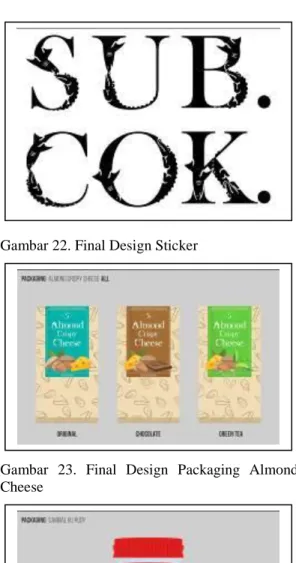
PERANCANGAN TYPEFACE
BERTEMAKAN SIMBOL IKAN SURA DAN BUAYA KOTA SURABAYA
Abstrak
Surabaya merupakan kota yang memiliki latar belakang budaya dan seni yang sangat kental. Kesenian khas kota Surabaya seperti Ludruk, Gending Jula-Juli Suroboyo, Tari Remo, Kentrung, Okol, Seni Ujung, Besutan, Upacara Loro Pangkon, Tari Lenggang Suroboyo dan Tari Hadrah Jidor semakin berkembang menjadikan kesenian tradisional dan modern saling melengkapi membentuk keragaman kesenian kota Surabaya. Di zaman modern ini kesenian visual di kota Surabaya seperti halnya seni tipografi semakin berkembang pesat. Tipografi merupakan mengalami perkembangan secara variatif . Tidak hanya pembuat tipografi vernacular yang bentuk tipografi tersebut bukanlah jenis tipografi yang dihasilkan melalui proses komputerisasi atau berasal dari jenis huruf (typeface) yang sudah ada melainkan bentuk tipografi yang dihasilkan oleh masyarakat sekitar dengan cara manual, tipografi yang melalui proses komputerisasi atau typeface mulai banyak di ciptakan oleh masyarakat kota Surabaya. Namun dari sekian banyak pembuat tipografi vernacular atau typeface di Surabaya masih jarang yang mengangkat tema Surabaya sebagai gagasannya. Perancangan typeface dengan menggunakan simbol ikan sura dan buaya kota Surabaya sebagai gagasannya ini bertujuan untuk Memperkenalkan kota Surabaya kepada masyarakat lokal maupun internasional melalui tipografi dan untuk memperkaya bentuk typeface di Indonesia.
Kata Kunci : Typeface, Tipografi, Simbol Kota Surabaya Abstract
Surabaya is a city that has an authentic cultural background. The cultural product from Surabaya such as Ludruk, Gending Jula-Juli Suroboyo, Tari Remo, Kentrung, Okol, Seni Ujung, Besutan, Upacara Loro Pangkon, Tari Lenggang Suroboyo and Tari Hadrah Jidor have developed. Traditional and modern art are forming together into the diversity of art in Surabaya. Moreover, visual art in Surabaya such as typography has rapidly developed nowadays. Typography is a part of visual communication design. Currently, the form of typography is developing in a variation. People start to create both of vernacular typography which is a manual typography and typeface which is a typography that is made by computerization. However, there is only few of the typography creator use the theme of Surabaya as their ideas. Furthermore, typeface that uses the theme of Surabaya aims to introduce Surabaya into both local and international society. In addition, this typeface could enrich the variety of typography in Indonesia.
Keyword: Typeface, Typography, Symbol of Surabaya
PENDAHULUAN
Di Kota Surabaya, dikenal sebagai kota yang memiliki latar belakang budaya dan seni yang sangat kental, kesenian tradisional dan modern saling melengkapi membentuk keragaman kesenian Kota Surabaya. Ludruk menjadi maskot budaya khas Kota Surabaya, terutama tari Ngeremonya. Ludruk sudah ada sejak zaman Jepang sekitar tahun 1942. Dan menjadi sangat popular di Kota Surabaya sejak zaman revolusi. Kesenian khas Kota Surabaya yang lainnya seperti Gending Jula-Juli Suroboyo, Tari Remo, Kentrung, Okol, Seni Ujung, Besutan, Upacara Loro Pangkon, Tari Lenggang Suroboyo dan Tari Hadrah Jidor. Upaya untuk mewujudkan kehidupan berkesenian di Kota Surabaya dikembangkan Dewan Kesenian Surabaya (DKS) maupun perkumpulan-perkumpulan seni theater, seni lukis dan musik. Pameran seni lukis maupun theater seringkali diselenggarakan di Gedung Balai Pemuda.
Sementara pagelaran seni tari tradisional selalu digelar di Taman Hiburan Rakyat (THR) dan Taman Budaya.
Pada zaman modern ini kesenian visual di Kota Surabaya seperti halnya seni tipografi semakin berkembang pesat. Tipografi merupakan bagian dari disiplin ilmu desain komunikasi visual. Pada masa urban, bentuk-bentuk tipografi mengalami perkembangan secara variatif yang sebagian besar dapat ditemui di sepanjang jalan bahkan di setiap gang-gang. Dimana sebagian bentuk tipografi tersebut bukanlah jenis tipografi yang dihasilkan melalui proses komputerisasi atau berasal dari jenis huruf (typeface) yang sudah ada, melainkan bentuk tipografi yang dihasilkan oleh masyarakat sekitar dengan cara manual. Bentuk tipografi semacam ini disebut dengan tipografi vernacular. Para pembuat tipografi vernacular tersebut bukan dari akademisi seni rupa desain melainkan belajar secara otodidak. Tipografi-tipografi vernacular yang dibuat oleh pembuat tipografi otodidak memiliki keunikan tersendiri, juga dapat
mempresentasikan kekayaan budaya suatu wilayah. Pada kenyataannya jenis tipografi semacam ini kadang hanya dipandang sebelah mata oleh masyarakat, karena masyarakat menilai dari segi informasinya saja, padahal bentuk-bentuk tipografi semacam ini merupakan kekayaan intelektual yang harus dihargai dan dilindungi.
Di Kota Surabaya sering ditemui pula jenis tipografi vernacular. Tidak hanya pembuat tipografi vernacular, tipografi yang melalui proses komputerisasi atau typeface mulai banyak diciptakan oleh masyarakat Kota Surabaya. Namun dari sekian banyak pembuat tipografi vernacular atau typeface di Kota Surabaya masih jarang yang mengangkat tema Kota Surabaya sebagai gagasannya. Adapun yang mengangkat tema Kota Surabaya sebagai inspirasi pembuatan typeface yaitu mahasiswa jurusan Desain Komunikasi Visual (DKV) Universitas Kristen (UK) Petra Surabaya, yang mengangkat 31 kecamatan seperti Tandes dan Genteng di Kota Surabaya menjadi Typeface dekoratif. Dari Kota Jakarta ada mahasiswa Program Studi Desain Komunikasi Visual (DKV), Universitas Indraprasta PGRI merancang typeface aksara latin berkarakteristik ondel-ondel budaya Betawi. Di Kota Semarang ada perancangan typeface yang mengangkat heritage ikonik seperti Lawang Sewu, Tugu Muda dan Sam Poo Kong yang dirancang oleh mahasiswa Desain Komunikasi Visual (DKV) Fakultas Arsitektur dan Desain Universitas Katolik Soegijapranata. Melihat permasalahan tersebut, maka penulis bertujuan untuk merancang TypeFace bertemakan simbol ikan sura dan buaya Kota Surabaya sebagai gagasannya, dengan tujuan untuk semakin memperkenalkan Kota Surabaya kepada masyarakat lokal maupun internasional melalui tipografi dan untuk memperkaya bentuk typeface di Indonesia.
RUMUSAN MASALAH
Bagaimana merancang typeface dengan menggunakan simbol ikan sura dan buaya Kota Surabaya sebagai gagasannya?
Sejarah Kota Surabaya
Nama "Surabaya" muncul pada era Majapahit awal. Nama itu secara lokal diyakini berasal dari kata Sura atau Suro (hiu) dan Baya atau Boyo (buaya), dua makhluk yang dalam mitos lokal, berperang satu sama lain untuk mendapatkan gelar "hewan terkuat dan paling kuat". Menurut Kuwarasan (2013:4) menjelaskan bahwa simbol Sura (hiu) dan Baya (buaya) sebenarnya untuk menggambarkan peristiwa heroik yang terjadi di Ujun g Galuh (nama terakhir dari Surabaya), yang merupakan pertempuran antara tentara yang dipimpin oleh raden widjaja dan tentara pasukan Tar tar pada tanggal 31 Mei 1293. Tanggal ini yang kemudian diperingati sebagai hari jadi Kota Surabaya.
Simbol Kota Surabaya Simbol Pertama
Gambar 1.
Simbol Kota Surabaya pertama kali tahun1848. Sumber: Badan Arsip dan Perpustakaan (BArous)
Pemerintah Kota Surabaya
Simbol Kota Surabaya pertama kali dibuat pada tahun 1848 menggunakan gambar ikan hiu dan buaya yang terlihat berjajar tetapi dengan posisi kepala yang berbeda. Simbol ini ditemukan dalam prasasti peringatan sepuluh tahun berdirinya perkumpulan music St. Caecilia, dan dalam surat kabar Soerabaiasche Courant, selain ditemukan juga yang menjadi ornament menara pantau Sjahbandar berada di bekas Pelabuhan Kalimas di depan Pasar Pabean.
Simbol Kedua
Gambar 2. Simbol Kota Surabaya yang ke-2 tahun 1906.
Sumber: Badan Arsip dan Perpustakaan (BArous)Pemerintah Kota Surabaya
Pada Simbol Surabaya yang ke-2 pada masa Kolonial Belanda tahun 1906 telah terlihat pertama kalinya kata „Soera Ing Baya‟. Kata „Soera Ing Baya‟ ini berasal dari Bahasa Jawa yang berarti „Berani melawan bahaya‟. Bentuk Simbol di masa ini terlihat mengikuti lambang di Eropa (Belanda) saat itu yang terdiri dari dua ekor singa yang mencengkeram gambar Suro dan Boyo yang berada dalam perisai.